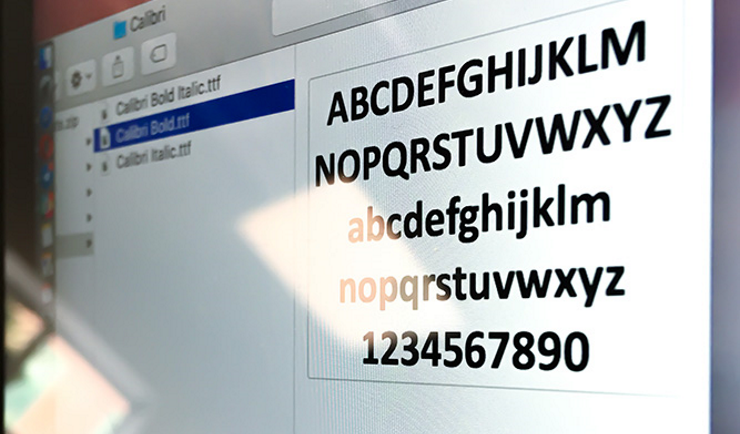
Дочь премьер-министра Пакистана Марьям Наваз подозревают в подделке документов, с помощью которых она пыталась доказать его непричастность к коррупции.
Марьям Наваз предоставила следователям документы, которые должны были доказать законность приобретения имущества её отцом Шарифом Навазом. Документы датировались 2006 годом, но специалисты определили, что они были набраны шрифтом Calibri, который компания Microsoft выпустила годом позже. Теоретически в документах мог использоваться этот шрифт, поскольку он был создан в 2004 году. Однако в состав пакета Microsoft Office (Word, PowerPoint, Excel и Outlook) и текстового редактора WordPad он был добавлен лишь в 2007 году. Теперь семье политика придётся объяснять следователям, каким образом шрифт появился у Наваза за год до официального релиза.
Премьер-министр Пакистана Шарифа Наваза подозревается в незаконном обогащении. Он занимает эту должность с 1990 года (с перерывом в 1999-2013 года). В 2016 году был опубликован «Панамский архив», в котором содержатся данные об имуществе политиков в разных странах, в том числе не задекларированном.